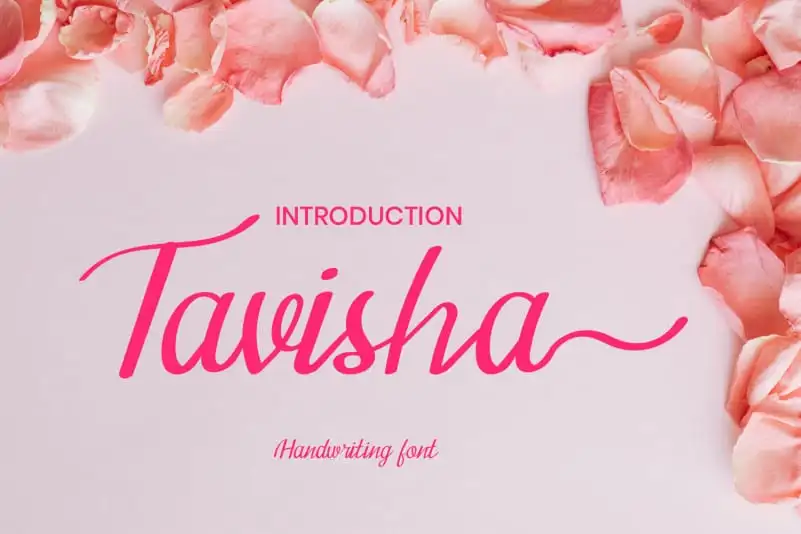
Tavisha Handwritten Font – Fonte Grátis
Tavisha Handwritten Font
A fonte Tavisha Handwritten é uma opção perfeita para aqueles que procuram um estilo natural e aconchegante para seus projetos digitais. Com seu traço delicado e fluido, essa fonte se destaca como o ideal para criar identidades visuais criativas e emotivas, desde as marcas de logotipos até cartões de festa e postagens sociais criativas. Suas linhas suaves e alegres fazem dela uma escolha ótima não apenas para seus designs mais formais, mas também para os mais íntimos e pessoais, como invitations de casamento ou cartas de cumprimentos. Tavisha Handwritten é uma fonte amigável que se adapta perfeitamente a muitos estilos gráficos, tornando-a uma escolha versátil para um leque variado de projetos digitais e impressos.